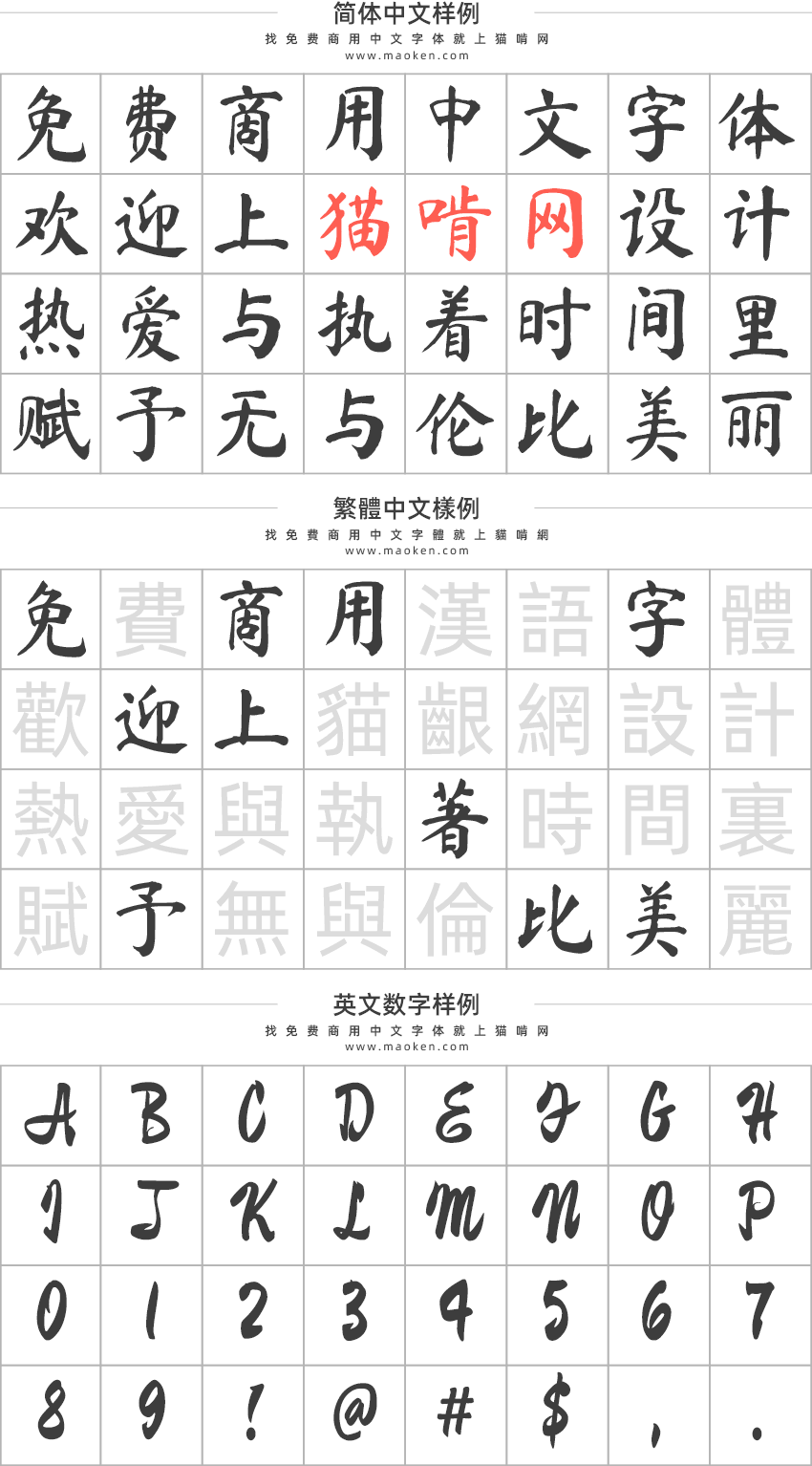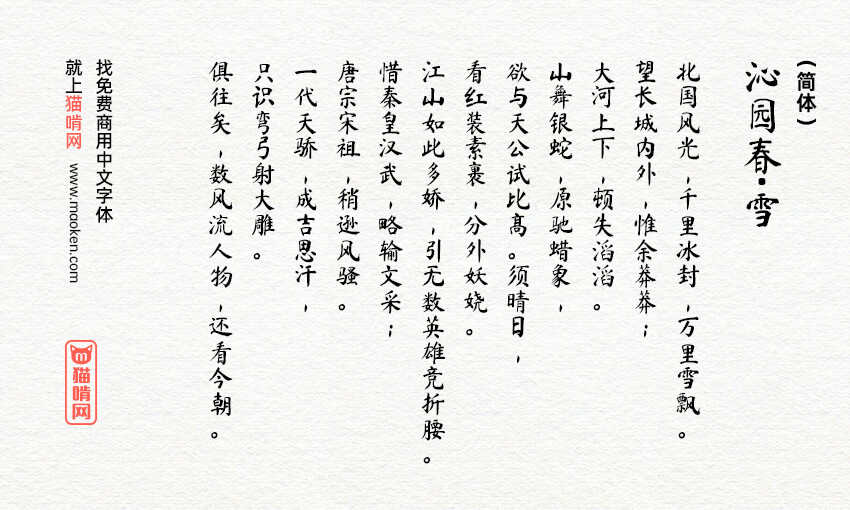
马善政毛笔楷书:还原毛笔墨韵质感的免费商用楷书字体
该字体由马善政(Ma ShanZheng)设计,风格让人联想到传统 “楹联” 所用字体 —— 楹联是贴于家门或寺庙门框两侧的短诗与吉祥祝语。字体兼具厚重雄伟之姿与舒展灵动之气。
马善政毛笔楷书是一款可以免费商用的简体毛笔字体,现在国内可以免费商用的毛笔字型并不多,比较常用的是庞门正道粗书体。现在终于又多了一款马山正毛笔体可以选择,真是太棒了!
勘误:马善政毛笔楷书v2.002: 高,将 二字仍为繁体写法
这款字体中文名称应该是【钟齐马善政毛笔楷书】吧,我安装后【字体库】显示的是【钟齐马善政毛笔楷书】
• 因为这款字体我是在谷歌开源字体项目上下载下来的,安装后PS中显示的名称是Ma Shan Zheng,所以名称我搞错了。稍后会进行更正,感谢你的指正~~